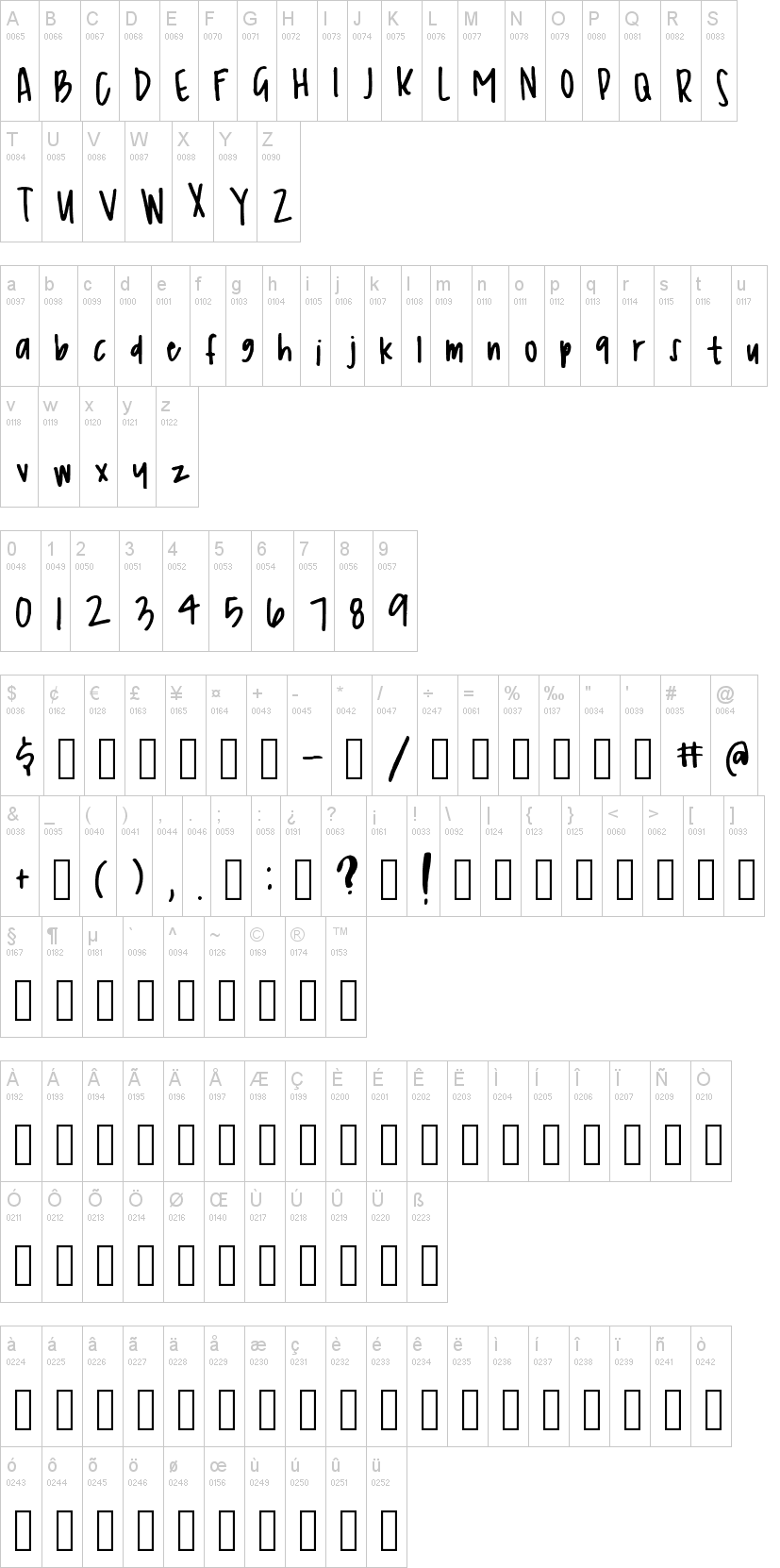
Simplicity 字体是一款简约风格的字体,它具有简洁、清新、现代的外观。它采用圆润的笔画,造型简单自然,易于阅读,适用于各种设计项目。它的字形结构紧凑,使用它可以节省空间,并且它的字体样式可以满足多种设计需求,可以满足您的多种设计需求。内容介绍
Simplicity是一款非常不错的手写艺术字体,具有很好的视觉感,适合于文化类的宣传设计、商业类品牌的广告和产品包装设计以及个性化文字排版等较多场景。